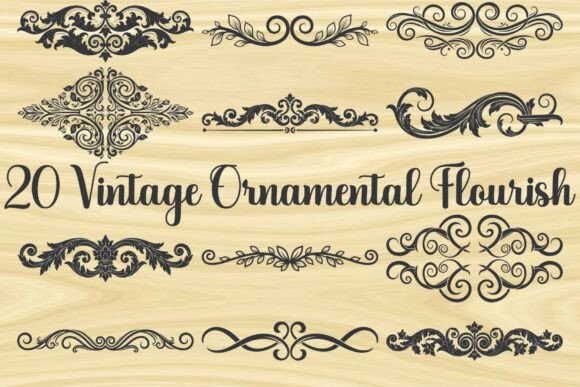
Vintage Ornamental Flourish
Si buscas recursos de alta calidad como Vintage Ornamental Flourish, este paquete premium es una opción fantástica para tus proyectos creativos.
Ya sea que estés creando productos POD (impresión bajo demanda), invitaciones de boda o gráficos para redes sociales, Vintage Ornamental Flourish es una opción ideal.